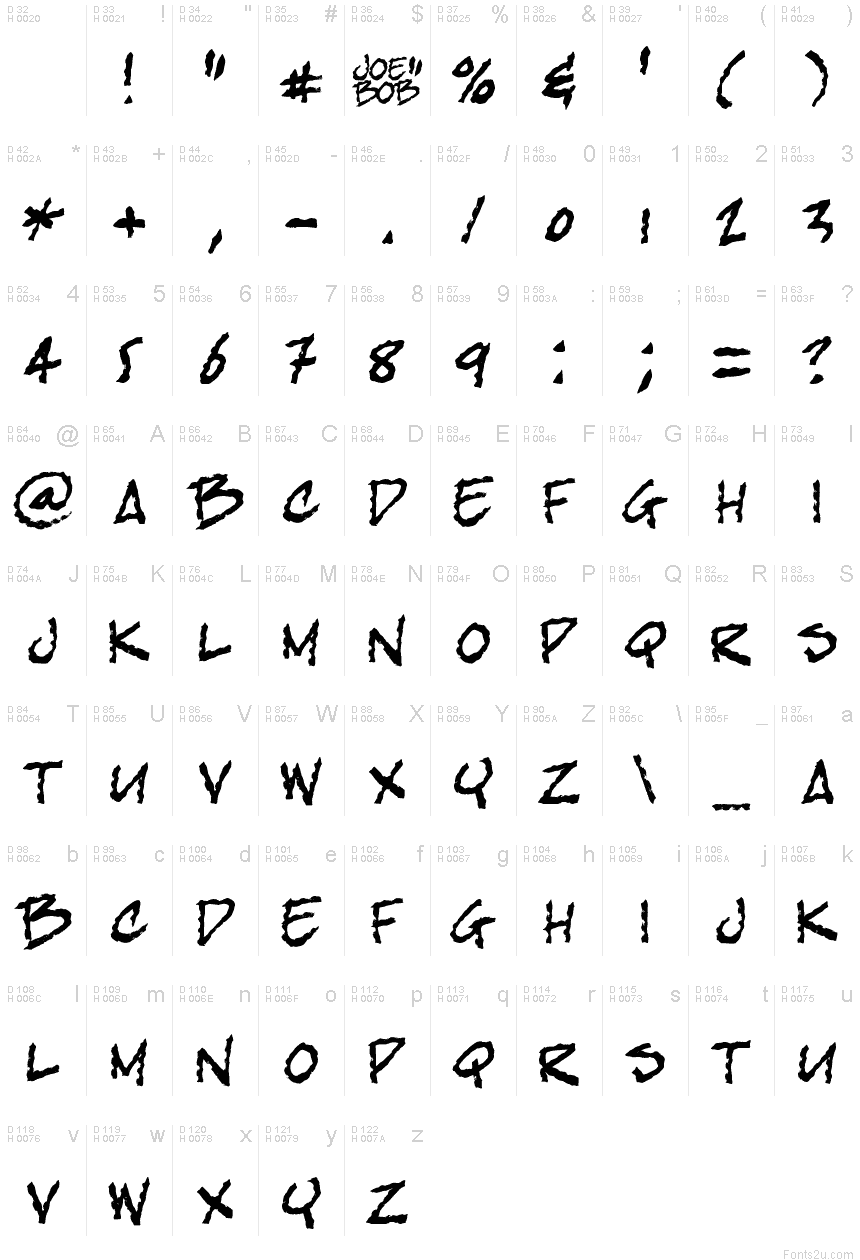
bobTag od joeBob graff-X to darmowy font typu brush, który wygląda, jakby został zerwany prosto z betonowej ściany. Litery sprawiają wrażenie nabazgranych grubymi, nasyconymi pociągnięciami, z surowymi krawędziami, nieoczekiwanymi kątami i dziką energią, która mimo wszystko tworzy spójne słowo. To kontrolowany nieład, który nadaje projektom ulicznego charakteru bez utraty czytelności.
Dzięki bobTag Twoje prace błyskawicznie zyskują surowy, miejski głos, idealny do plakatów koncertowych, zinów, brandingu skate czy streetwearu, horrorów, grafiki gier i odważnych postów w mediach społecznościowych. Ten darmowy font najlepiej sprawdza się w dużych rozmiarach – niech krzyczy w nagłówkach, a w tekstach uzupełniających połącz go z prostym, geometrycznym bezszeryfem.